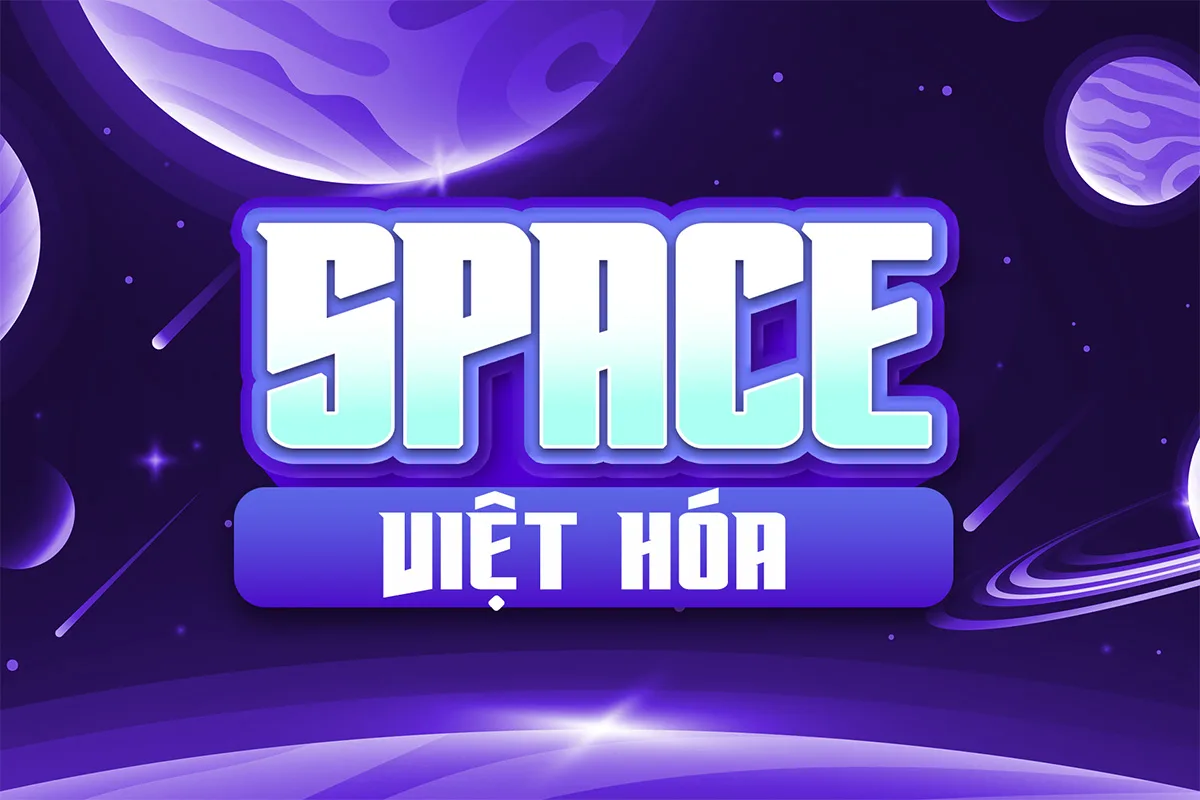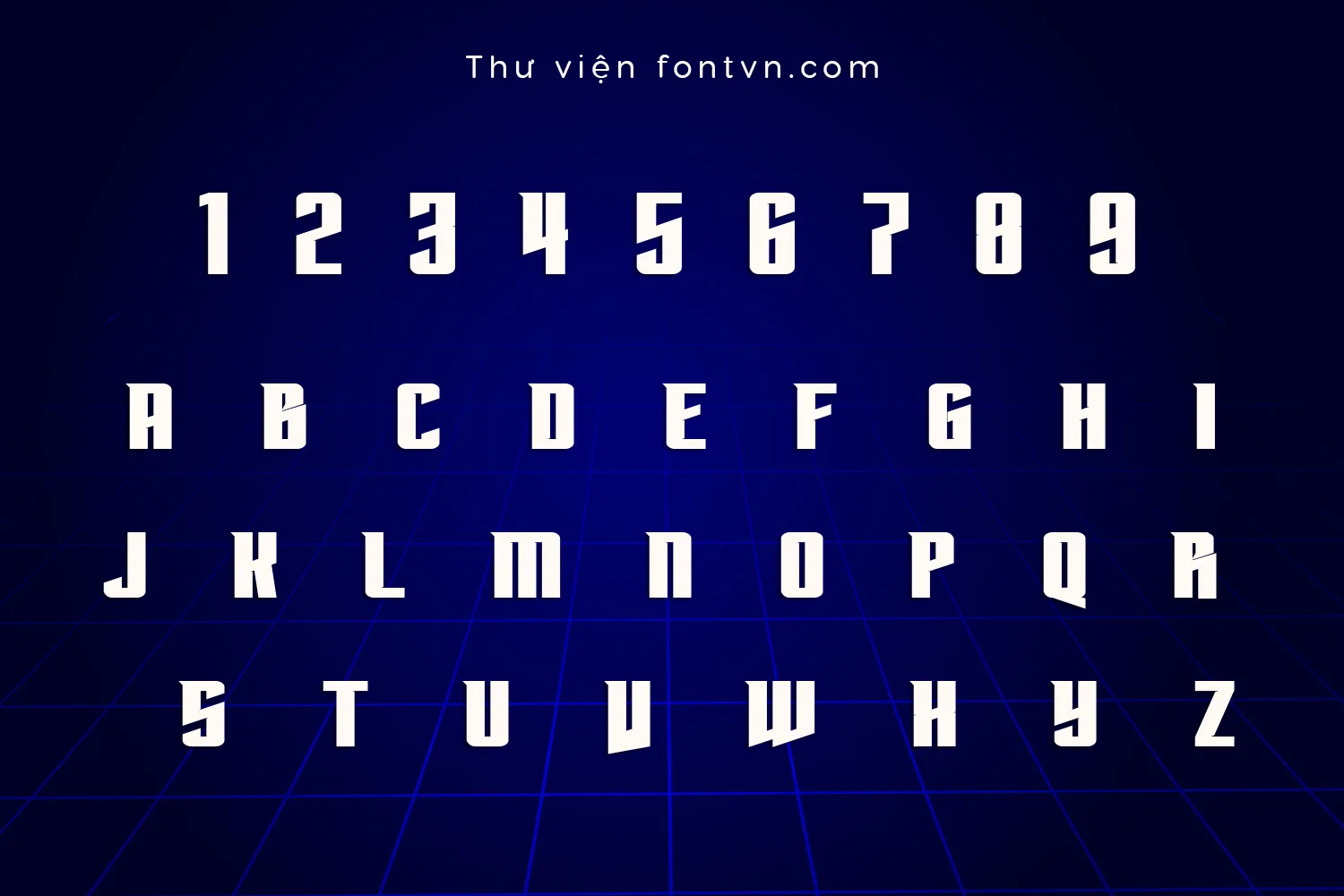
DVN SPACE – Font chữ viễn tưởng góc cạnh cho thiết kế tương lai
DVN SPACE là font chữ display mang phong cách sci-fi hiện đại, nổi bật với kết cấu nét thẳng, góc cắt sắc và hình khối hẹp. Các ký tự được thiết kế đồng đều, tạo cảm giác chắc chắn, công nghệ và có hơi hướng không gian – tương lai.
Điểm đặc trưng của DVN SPACE nằm ở những lát cắt chéo và khe hở có chủ đích, giúp chữ trông mạnh mẽ nhưng không thô, giữ được nhịp điệu thị giác rõ ràng khi đặt trong tiêu đề lớn hoặc logo. Bộ chữ in hoa và thường có tạo hình nhất quán, dễ kiểm soát bố cục và khoảng cách.
Font đặc biệt phù hợp cho logo game, poster sci-fi, công nghệ, esports, banner chủ đề không gian, cyber, futuristic brand hoặc các thiết kế cần cảm giác lạnh – mạnh – hiện đại. DVN SPACE phát huy tốt nhất khi dùng cỡ lớn, nền tối hoặc phối cùng hiệu ứng ánh sáng, neon, chrome.